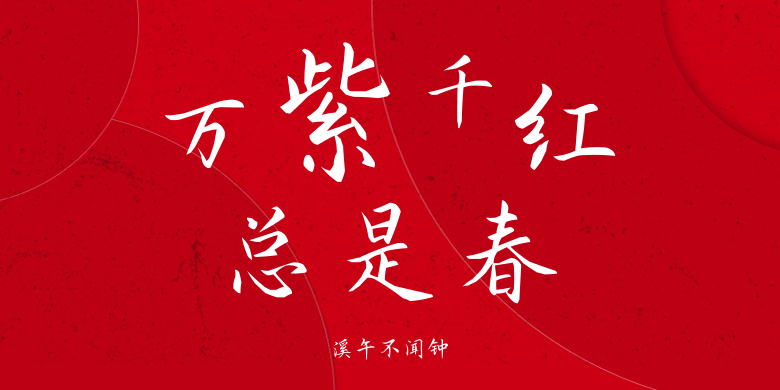
溪午不闻钟
溪午不闻钟,这款字体结构工整、笔画清晰,兼顾美观与易读性,适用于标题、正文、海报、包装、LOGO 等多种场景。字形优雅稳定,风格百搭耐看,适配日常排版与创意设计,让文字呈现更舒适、更具质感。溪午不闻钟一笔一画,皆是细节,以均衡的比例、流畅的线条打造舒适视觉体验,字形端正大气,风格简约现代。无论是商业设计、品牌宣传还是日常排版,都能轻松驾驭,让文字更有格调与力量。溪午不闻钟字体下载。